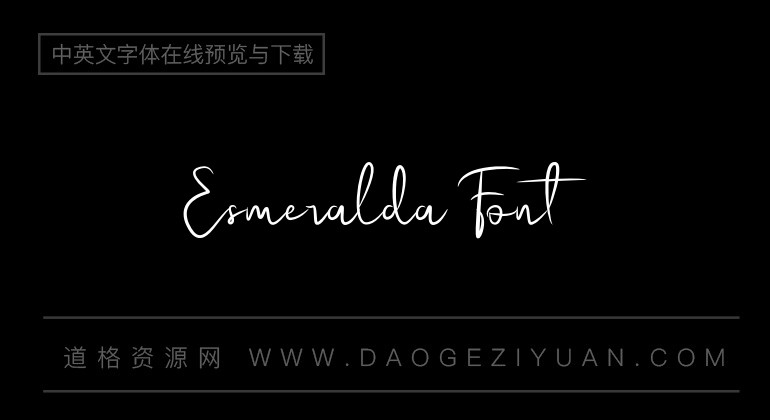
Esmeralda Font 是一种优美的手写风格字体。它具有轻盈的笔画和流畅的曲线,适用于多种应用场合,如标题、卡片、包装、海报、标志等。该字体的字形为单线条,字母之间的间距较大,使得该字体更加易于阅读和辨认。Esmeralda Font 中的字母和符号设计出色,如小写字母的“a”和“g”以及符号“&”和“#”等。该字体拥有多种字重和风格,使得用户可以根据需要选择不同的版本。总之,Esmeralda Font 是一种适用于多种设计项目的优秀字体。内容介绍
Esmeralda Font是一款非常不错的手写艺术字体,具有很好的视觉感,适合于文化类的宣传设计、商业类品牌的广告和产品包装设计以及个性化文字排版等较多场景。